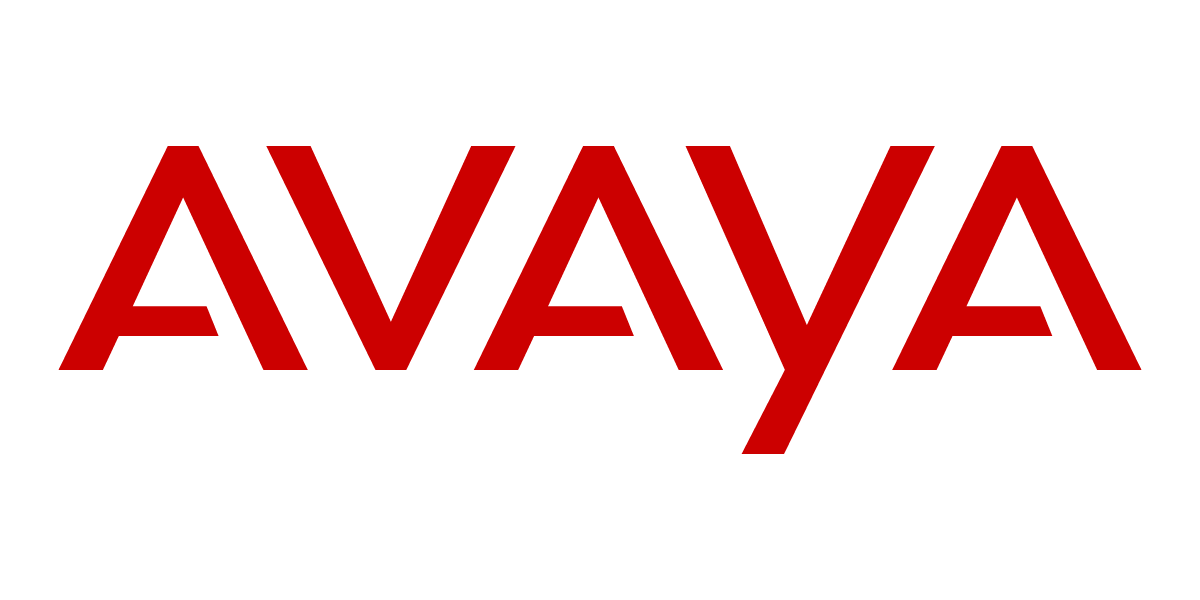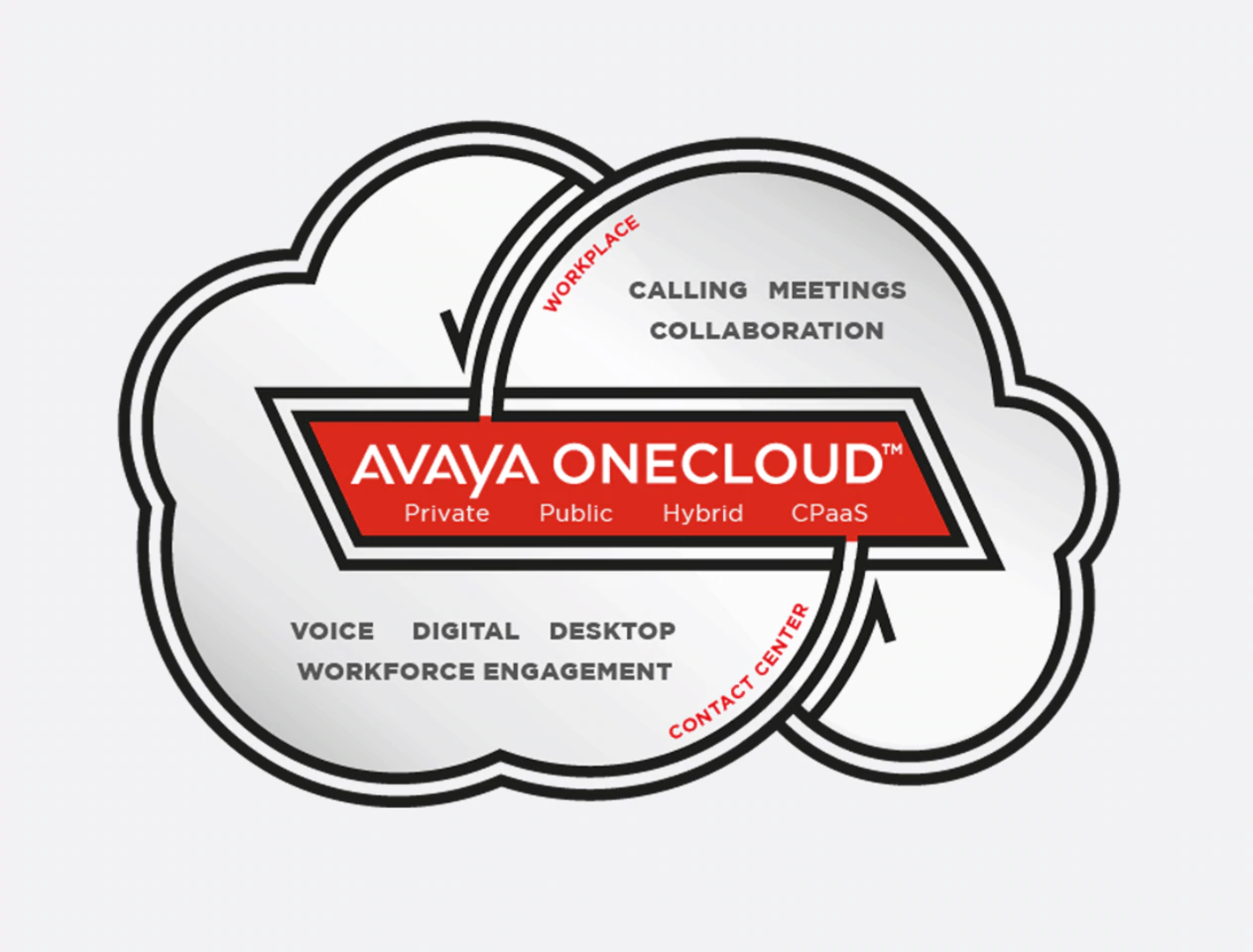
Avaya - Welche Schriftart?
Könnt ihr uns bitte helfen und welche Schriftart ist das? Bzw. habt ihr eine sehr ähnliche?
Geh mal davon aus, dass das Logo nicht aus einer "fertigen" Schrift gesetzt wurde, sondern für den Zweck des ReBrandings entworfen wurde. --> https://docplayer.net/30220886-Avaya-branding-guidelines.html
Was die ähnliche Schrift betrifft: Das sind natürlich nur relativ wenige Buchstaben, um hier eine Ähnlichkeit zu anderen Schriftarten  zu bestimmen. A und V sind vom Konstruktionsprinzip aus der Gruppe der serifenlosen Linear-Antiquas.
Oder suchst Du eher eine Schriftart, bei der der Querstrich vom A verkürzt ist?
Dann wäre das Stichwort Stencil vermutlich hilfreich bei der Suche.
Ah top schon mal danke und ja es wäre nur das A interessant. Die anderen Buchstaben soll ten "normal" sein.
Anbei noch ein Bild mit mehreren Buchstaben...
Ja, Gotham ist deren Hausschrift.
Das Logo basiert aber auf einer anderen Schrift oder ist komplett gestaltet/konstruiert. Die Gotham hab ich mal drübergelegt.